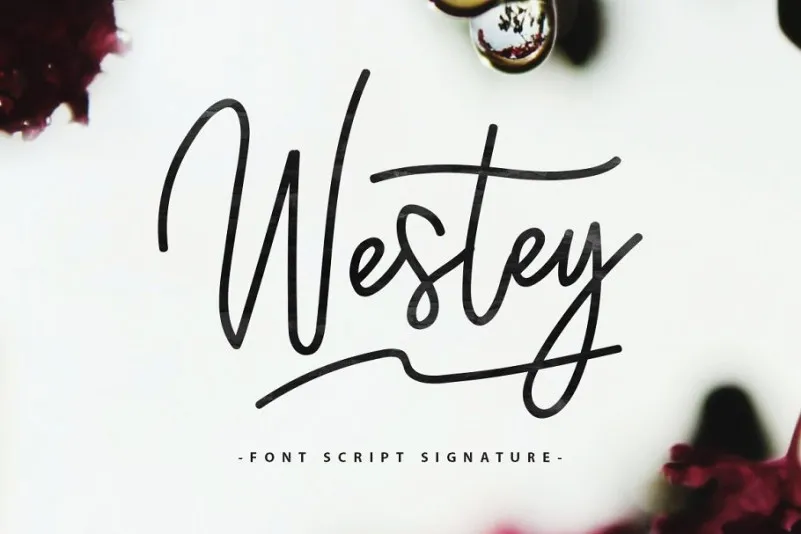
Westey Signature Font
A Westey Signature Font é uma opção única para designers que buscam um estilo elegante e delicado. Este tipo de script foi feito à mão e depois traceado com vida, criando formas únicas de assinatura, formando um belo estilo de escrita. A fonte é a criação do designer sizimon. Perfeito para cartões de casamento, logotipos, cabeçalhos de sites e até mesmo desenhos fashion, Westey oferece uma variedade impressionante de alternativas de gílias e caracteres swash, totalizando 136. Suporte multilíngue também é um dos destaques da fonte. Para designers a procura de algo autêntico e elegante para seus projetos, a Westey Signature Font certamente será uma ótima escolha. Sua beleza é perfeita tanto para o design básico quanto para projetos mais elaborados, tornando-a versátil em uma ampla gama de aplicações gráficas.